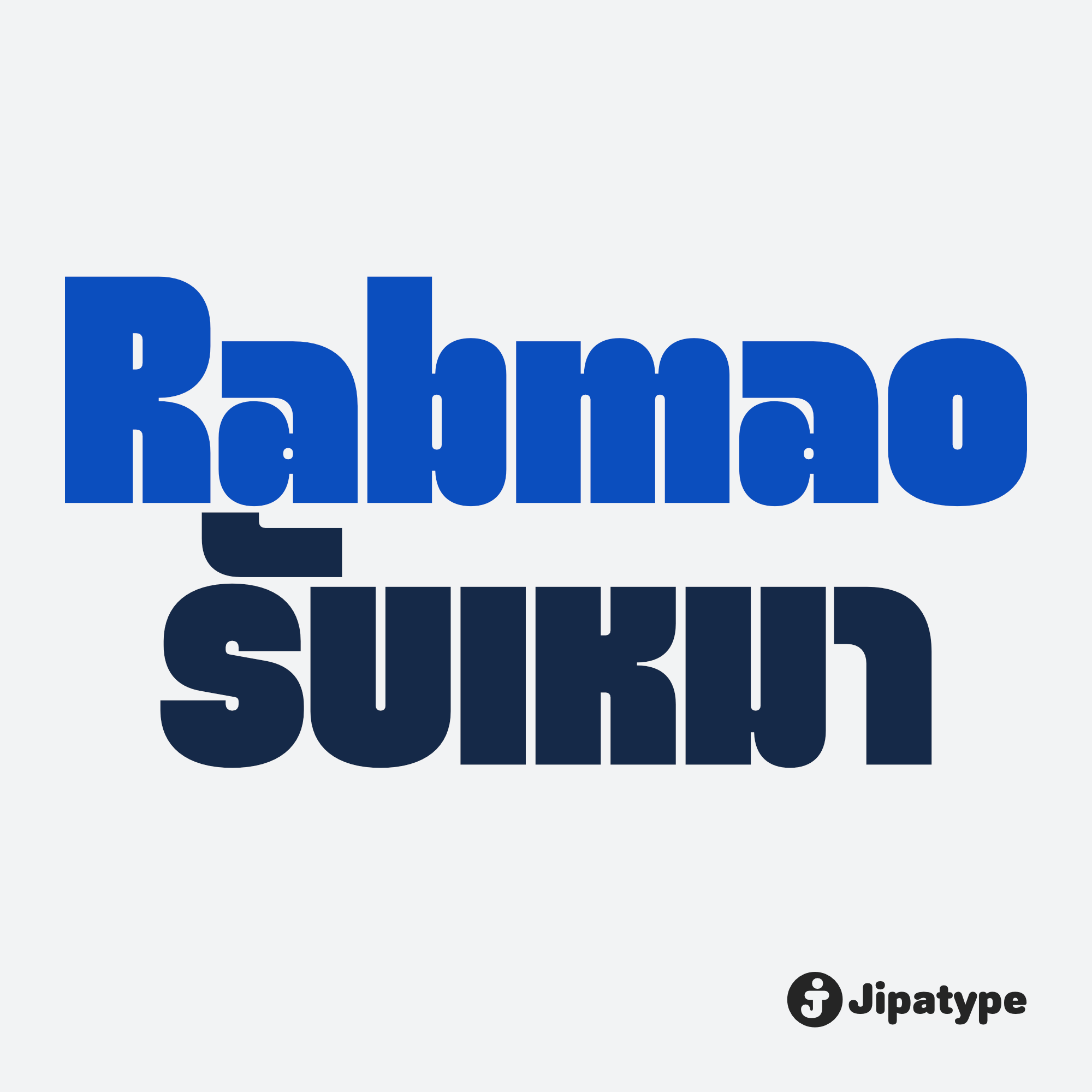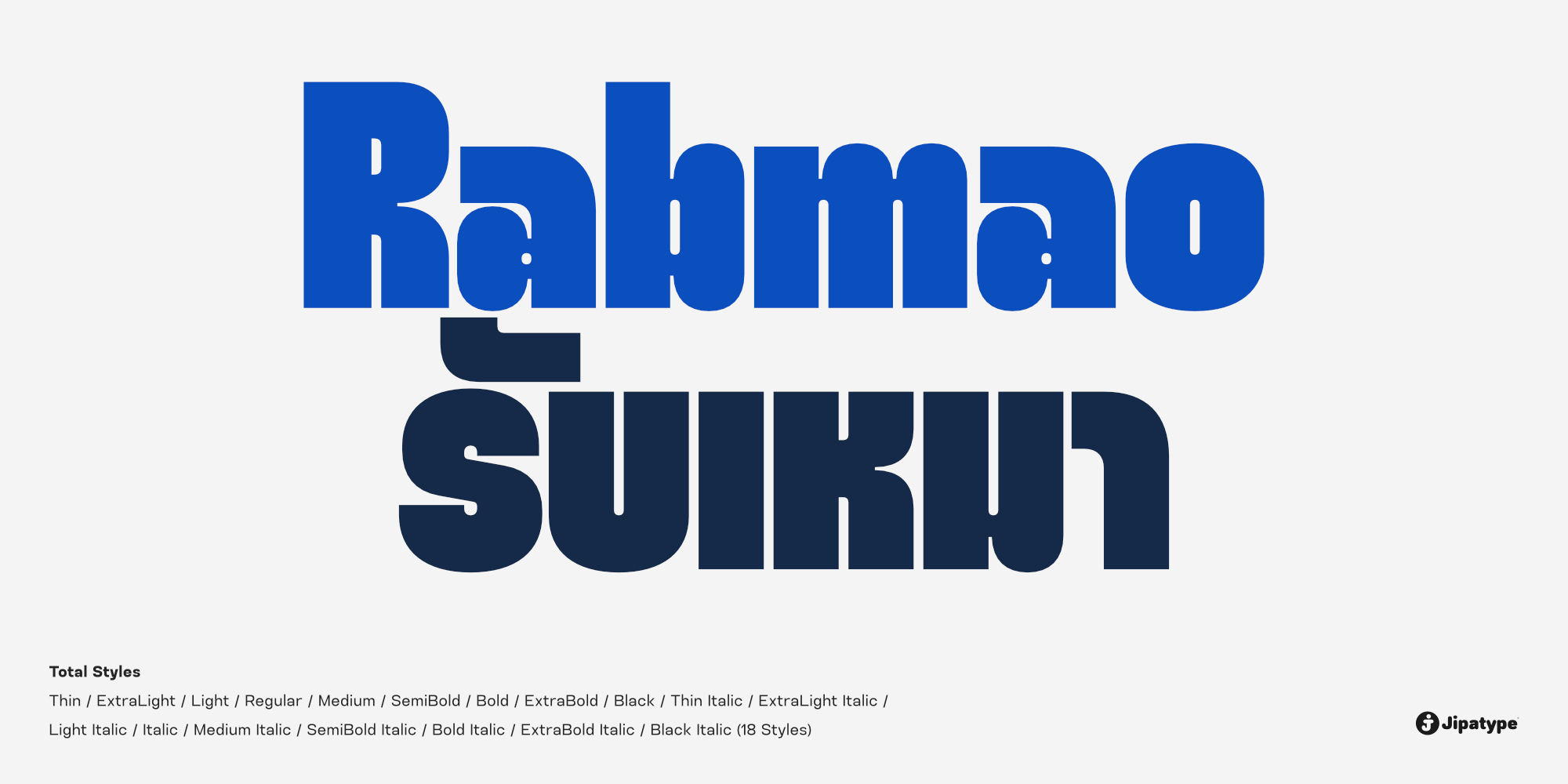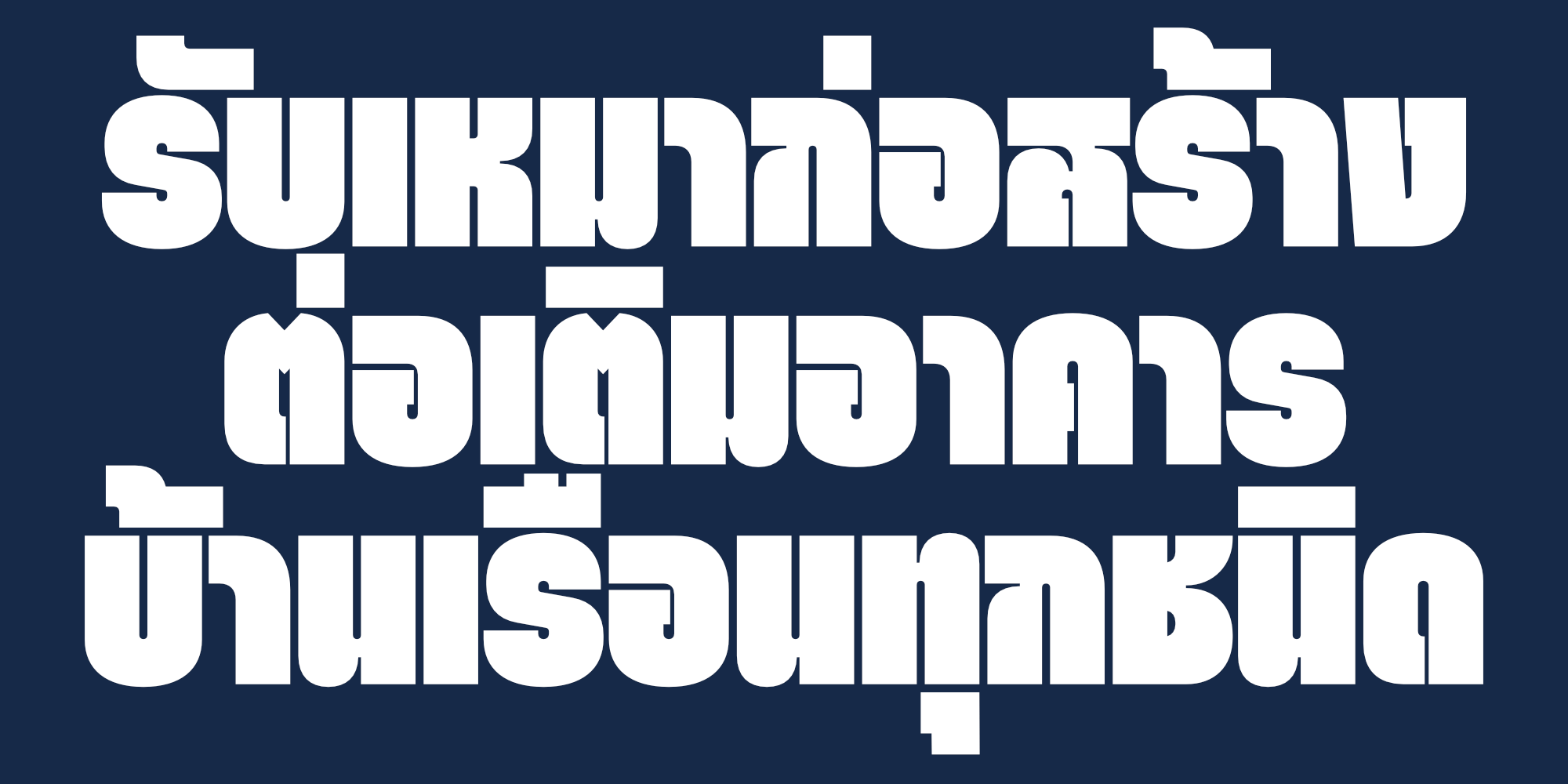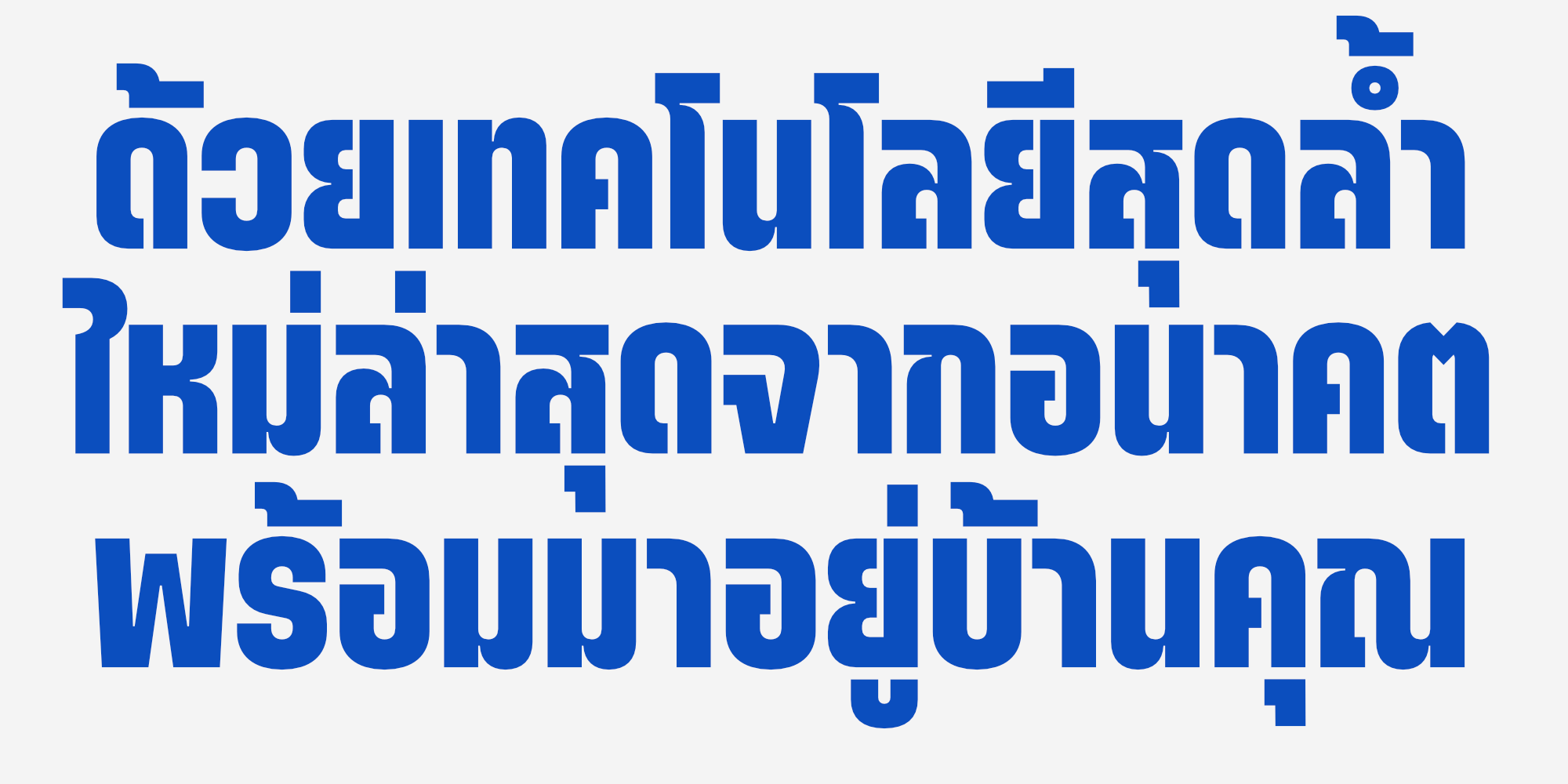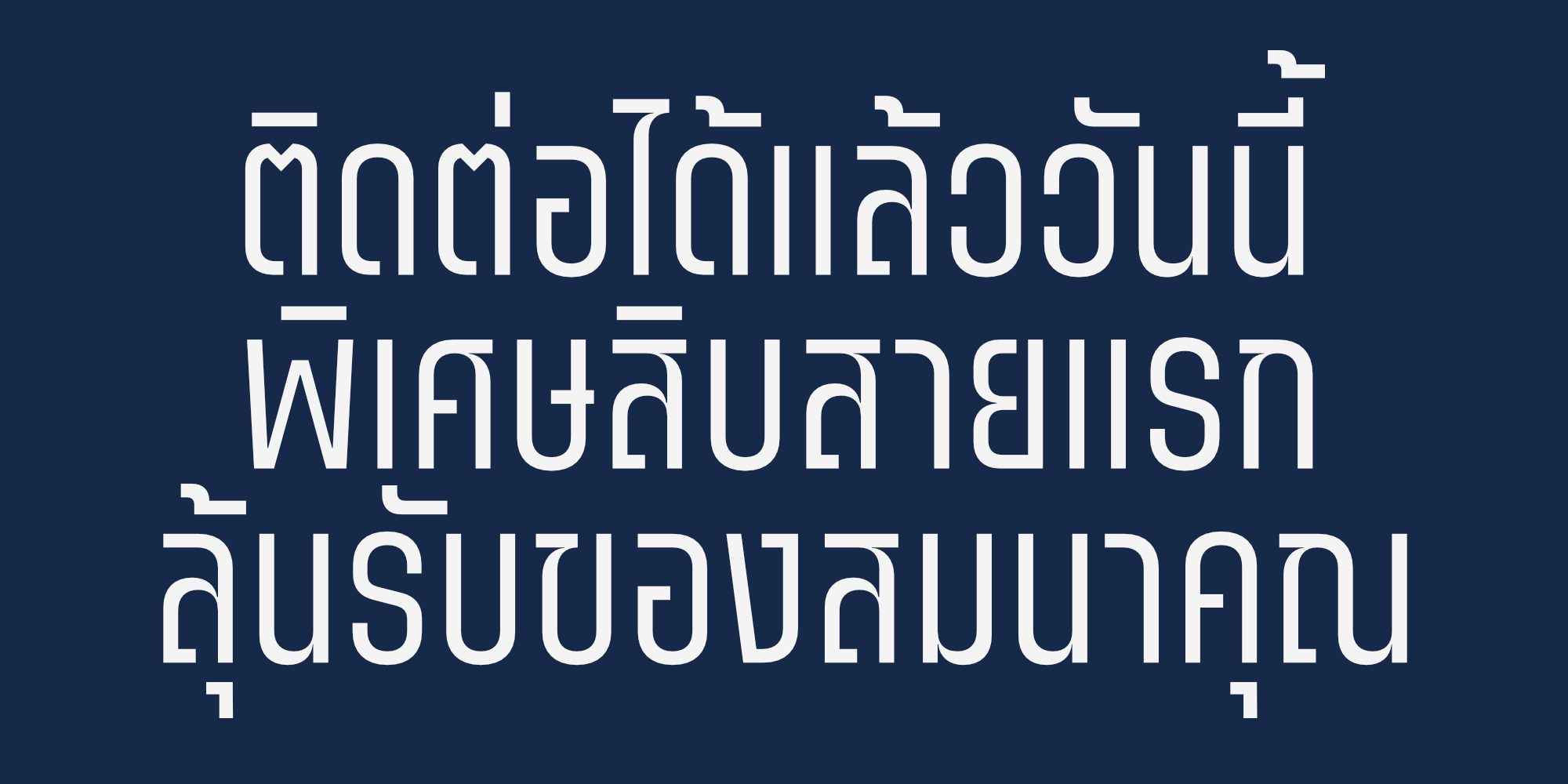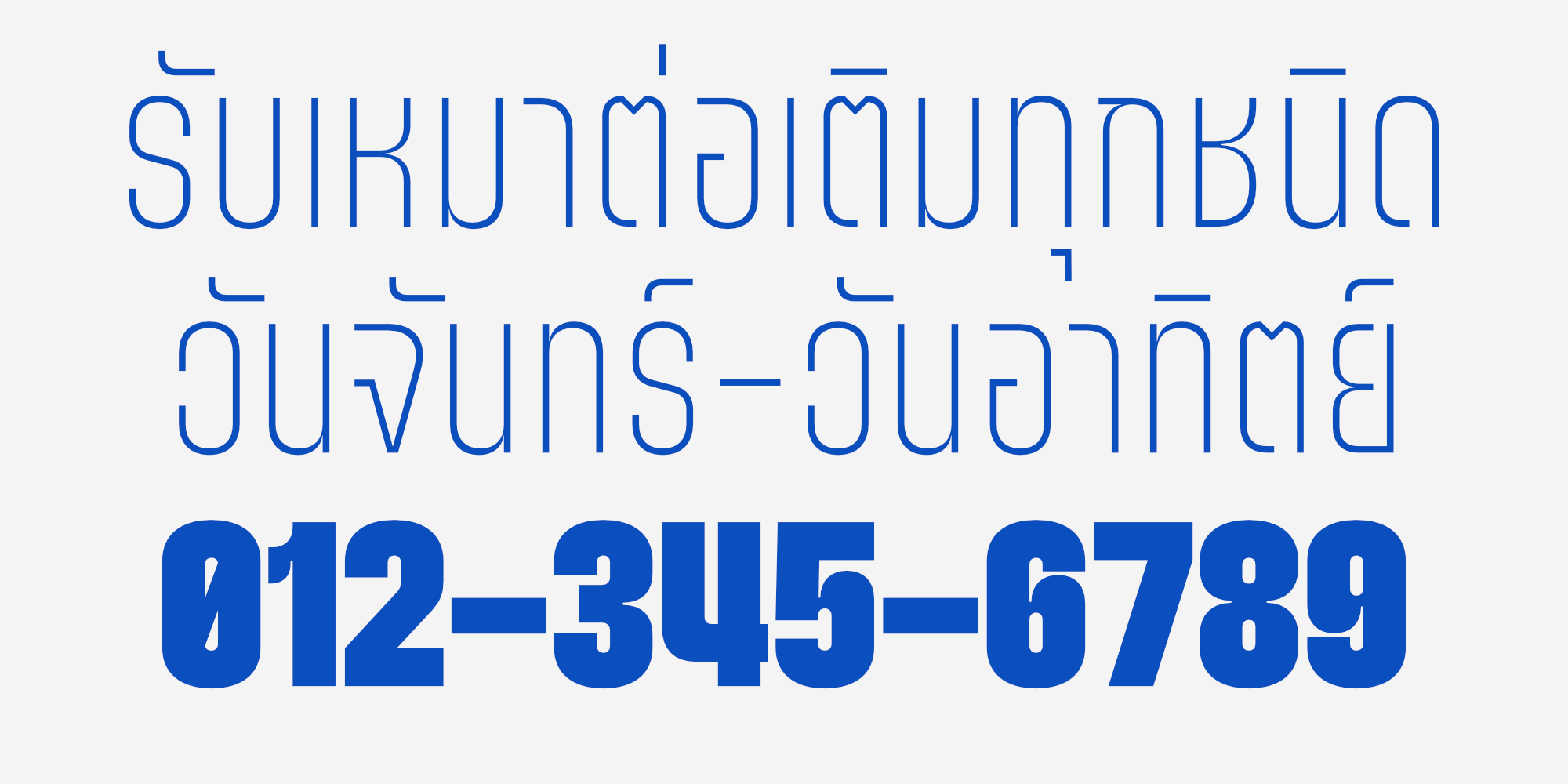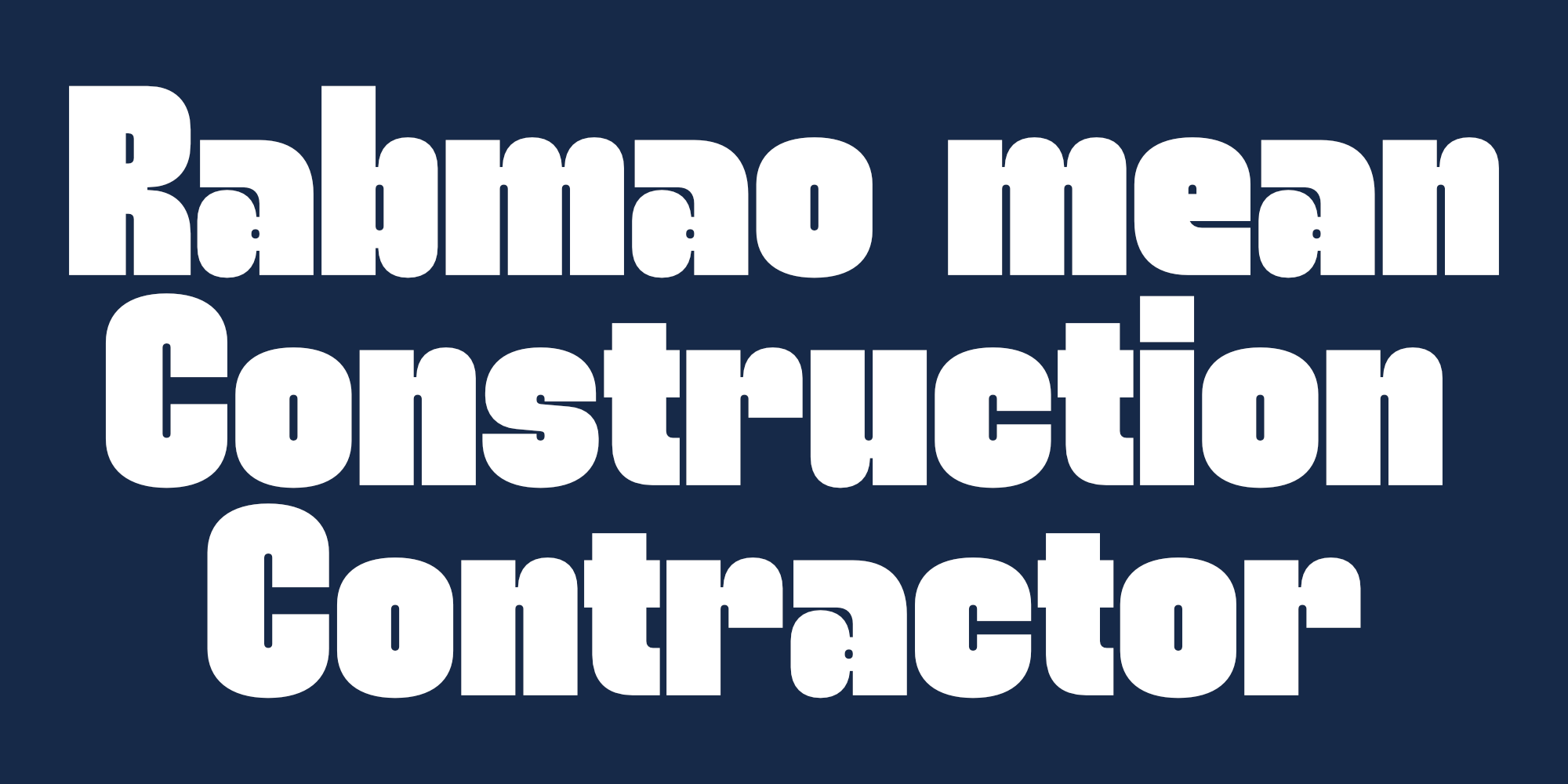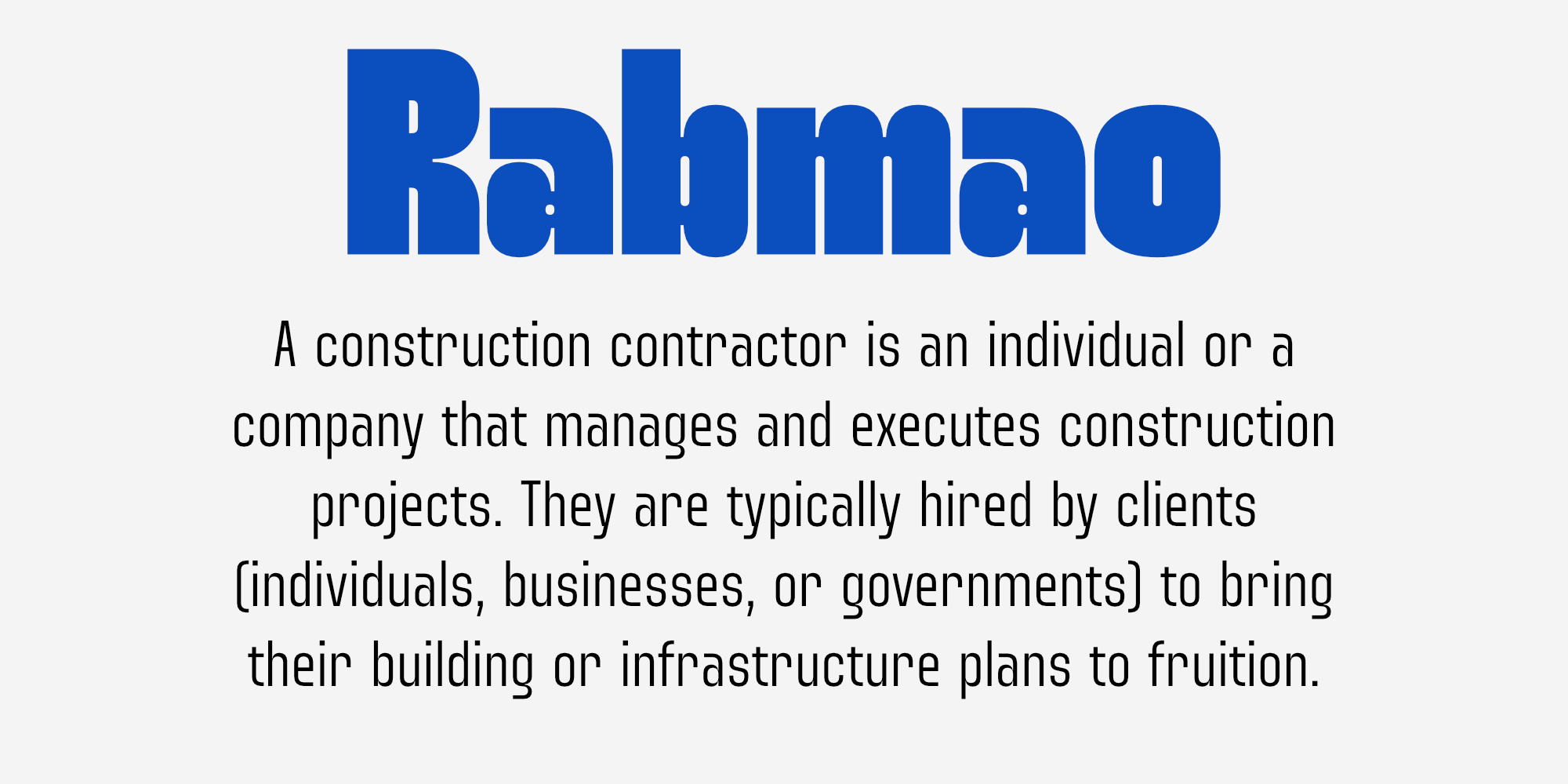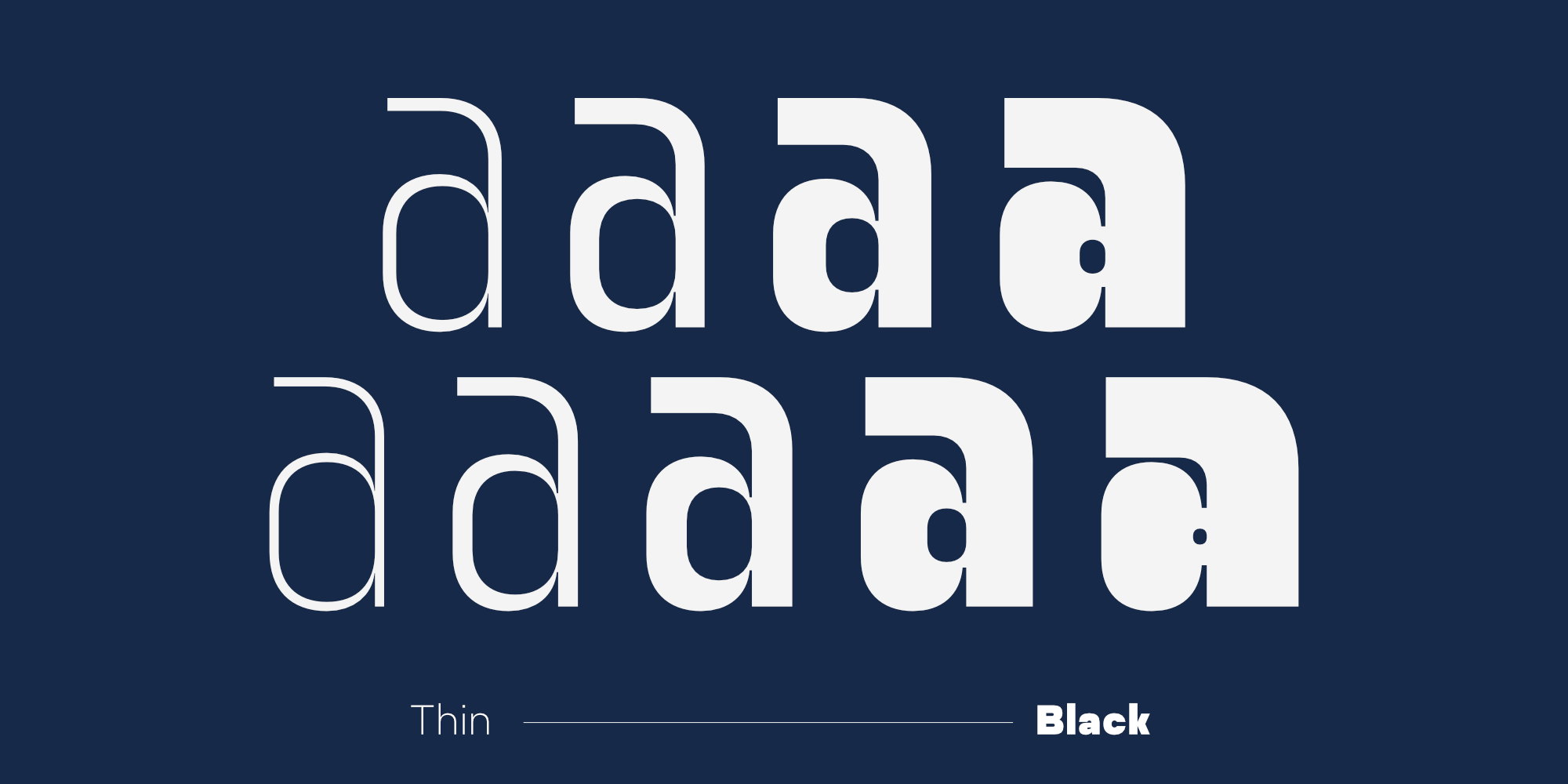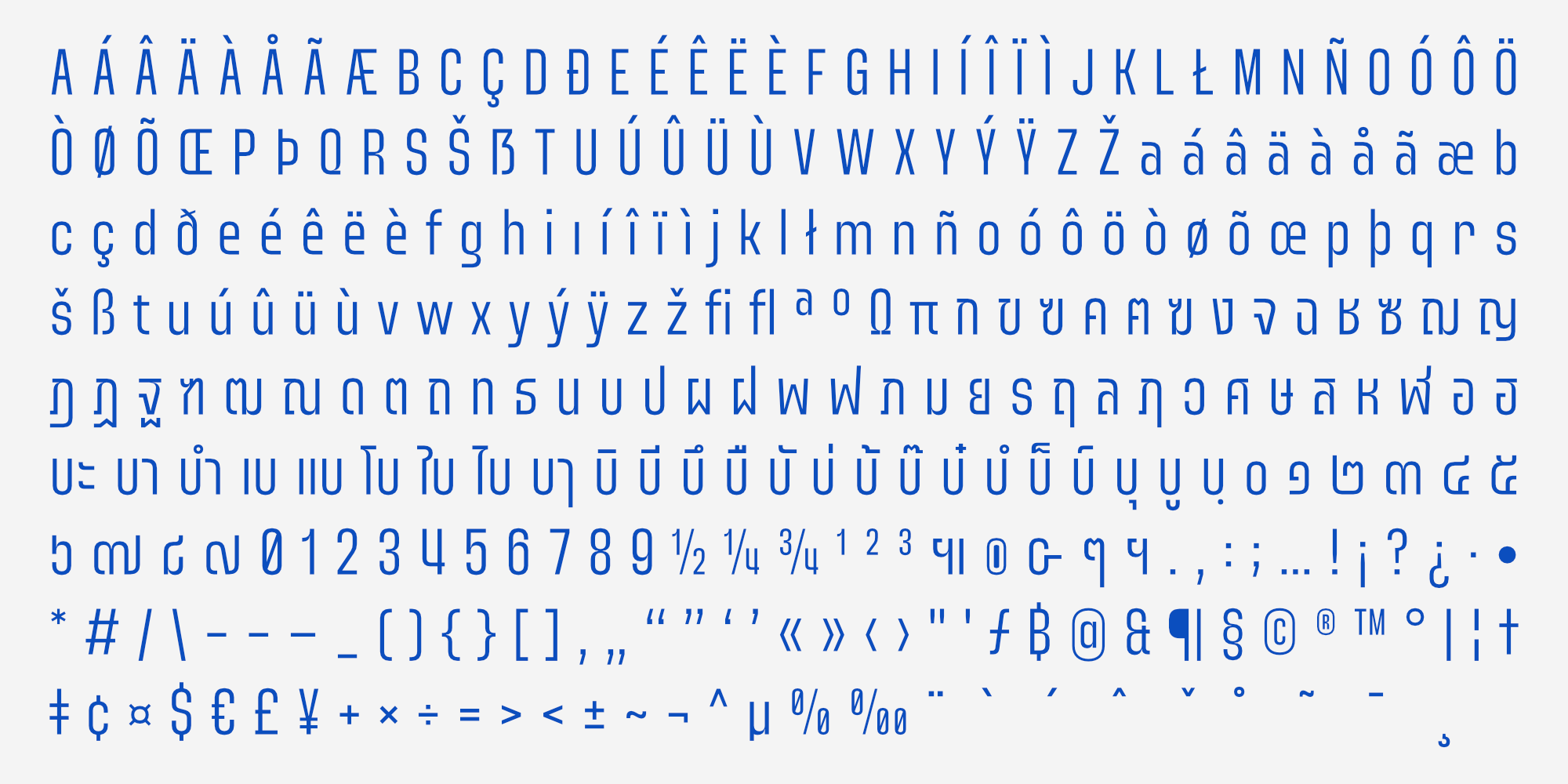
Rabmao เป็นชุดตัวอักษรประเภท Sans-serif สไตล์โมเดิร์นที่โดดเด่นด้วยโครงสร้างทรงเรขาคณิต ผสมผสานกับความโค้งมนที่ลงตัว ตัวอักษรถูกออกแบบให้มีความกว้างแบบ Condensed เล็กน้อย ช่วยให้ประหยัดพื้นที่ในการจัดวางแต่ยังคงอ่านง่าย
รูปแบบอักษรไทยเป็นดีไซน์แบบ “ไม่มีหัว” ที่ดูสะอาดตา ทันสมัย และมีความเป็นสากล จุดเด่นสำคัญอยู่ที่ความหลากหลายของน้ำหนัก ซึ่งให้อารมณ์ที่แตกต่างกันอย่างชัดเจน โดยน้ำหนักหนา จะมีลักษณะที่ตัน ทึบ และแข็งแรงทรงพลัง คล้ายกับโครงสร้างทางสถาปัตยกรรม ในขณะที่น้ำหนักบาง จะให้เส้นสายที่คมชัด โปร่งเบา และดูเรียบหรู
ด้วยบุคลิกที่ดูแข็งแรง มั่นคง แต่แฝงไปด้วยความเป็นมิตร Rabmao จึงเหมาะอย่างยิ่งสำหรับการใช้งานเป็น Display Font หรือพาดหัวหลัก ที่ต้องการสร้างจุดสนใจและแรงดึงดูดสายตา เช่น การออกแบบโลโก้, ป้ายโฆษณา, โปสเตอร์, บรรจุภัณฑ์สินค้า ไปจนถึงงานออกแบบอัตลักษณ์องค์กร ที่ต้องการภาพลักษณ์ที่ดูเป็นมืออาชีพ ทันสมัย และน่าเชื่อถือ
นอกจากนี้ ด้วยความที่มีน้ำหนักให้เลือกหลากหลาย จึงยังสามารถนำไปใช้กับส่วนเนื้อหา สื่อสิ่งพิมพ์ที่ต้องการความชัดเจนในการสื่อสารได้เป็นอย่างดี
ออกแบบโดย : อานุภาพ ใจชำนาญ (Anupap Jaichumnan)